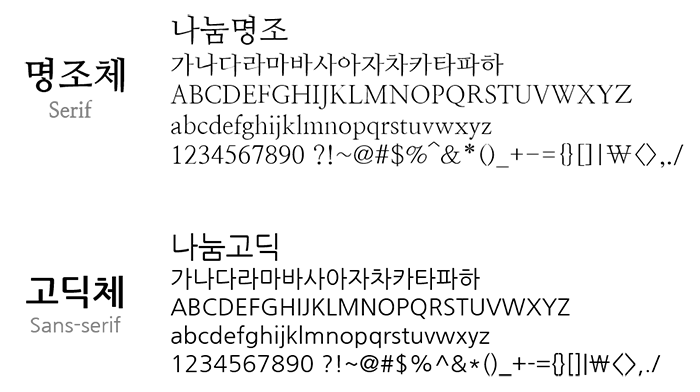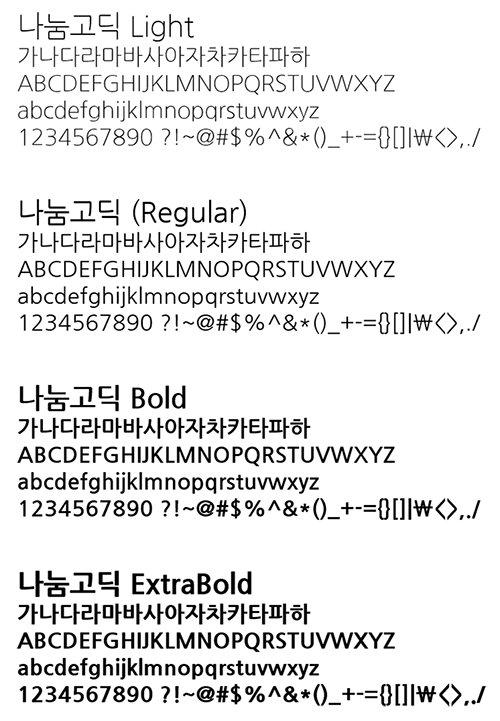
1. 폰트는 고딕체, 한 종류의 폰트만 사용!
1) 폰트는 고딕체를 사용하세요.
2) 폰트는 한 종류만 사용하세요.
2. 컬러(Color)는 흑백으로 시작해서 중요한 색상은 1~2개, 5~10%만 사용!
1) 컬러를 적용할 때는 처음부터 색을 적용하지 말고 흑백(B&W)으로 시작하세요.
2) 중요한 역할을 하는 요소에 중요한 컬러 1~2개, 그리고 5~10%만 사용하세요.
1. 폰트는 고딕체, 한 종류의 폰트만 사용!
디자인을 하는 데 있어서 글자에 어떤 폰트를 사용할지 고민하게 됩니다. 고딕체와 명조체 중? 그리고 어떤 폰트를? 선택할지 모르겠다면 아주 쉬운 방법은 고딕체 계열의 폰트, 한 종류만 사용하면 된다는 것입니다.
1) 폰트는 고딕체를 사용하세요.
보통의 경우 명조체와 고딕체 중 어떤 종류의 글자체를 사용해야 할지 고민된다면 고딕체를 사용하세요.
폰트는 크게 명조체와 고딕체로 나누어지는데 컴퓨터와 핸드폰이 보급되면서 디지털 환경에 친화적인 고딕체가 많이 사용되고 있습니다. 그래서 일반적으로 사용자에게 고딕체가 익숙한(Familiar) 글자체가 되었습니다.
[그림 1] 명조체와 고딕체
2) 폰트는 한 종류만 사용하세요.
고딕체 계열의 폰트 한 종류만 사용한다는 것은 예를 들어 “나눔고딕”만을 사용하면 된다는 것입니다.
폰트 한 종류의 의미는 지정한 폰트의 세트를 말합니다. 대부분의 폰트는 보통 Light, Regular, Bold 등의 세트로 구성되어 있습니다.
예를 들어 [그림 2]와 같이 나눔고딕을 보면 나눔고딕 Light, 나눔고딕 (Regular), 나눔고딕 Bold, 나눔고딕 ExtraBold가 한 세트로 구성되어 있습니다.
[그림 2] “나눔고딕” 타이프페이스(Typeface)
이러한 폰트의 세트 또는 폰트 패밀리를 “타이프페이스(Typeface)“라고 하는데 중요한 것은 글자 역할의 중요도에 맞춰서 타이프페이스(Typeface)에서 적절한 폰트를 골라서 적용해주는 것입니다.
[그림 3] 폰트의 적용 사례
“[그림 3] 폰트의 적용 사례”를 보면 왼쪽의 디자인은 너무 많은 종류의 폰트를 사용한 예입니다.
오른쪽의 디자인은 한 종류의 폰트인 나눔고딕 세트 , 즉 “나눔고딕 타이프페이스(Typeface)”만을 사용한 예입니다. 그리고 글자의 역할의 중요도에 맞춰 제목, 소제목, 키워드에는 나눔고딕 Bold를 본문에는 나눔고딕을 사용하였습니다.
너무 많은 종류의 폰트를 사용하지 마세요! 한 종류의 폰트(Typeface)로도 충분합니다!
그리고 명조체를 사용해도 됩니다! 한 종류의 폰트, 즉 하나의 타이프페이스(Typeface)를 사용하는 것이 비전공자와 초보자가 아주 쉽게 좋은 디자인을 할 수 있는 방법인 것입니다.
[그림 4] 명조체와 고딕체 타이프페이스(Typeface) 적용 사례
현재 디지털 기술의 발전으로 인하여 고밀도/고해상도 디스플레이가 보급되면서 앞으로는 명조체 또한 많이 사용될 것으로 예상됩니다.